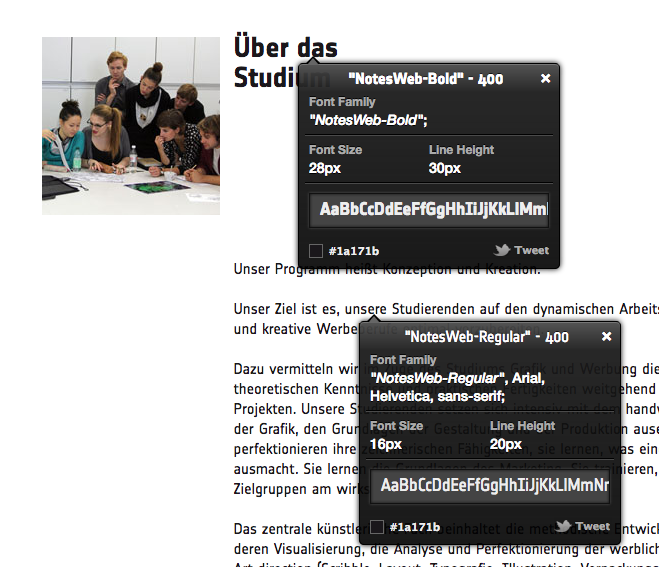
Welche Font ist auf dieser Homepage? (Klasse für Ideen)
Ich habe mir überlegt meinen Text bei meiner Bewerbung an deren Homepage anzulehnen. http://www.klassefuerideen.at/Studium.6.0.html
Dazu hätte ich aber 2 Fragen:
1. Um welche Schriftart handelt es sich hier bei Überschriften und Fließtext?
2. Empfindet ihr die Schrift als passend für die Bewerbungsmappe?
Ich bin mir nicht im klaren ob diese nicht vordergündig wegen der Lesbarkeit auf  Monitoren gewählt wurde. Persönlich spricht sie mich nicht so an, wirkt irgendwie kühl auf mich. Ich tue mir aber noch sehr schwer Schriften richtig zu beurteilen.
Selbst würde ich vermutlich die Open Sans Semibold oder Cambria wählen. Was haltet ihr davon?
"NotesWeb-Bold" und "NotesWeb-Regular".
Ich vermute eher weil Sie auch im Logo verwendet wird.
Gegen Deine Vorschläge spricht nichts, probiers doch mal aus ...
Ja genau es geht um den Einsatz in meiner Bewerbungsmappe also im Print.
Ich habe habe mich vorläufig mal für die cambria entschieden da sie mich mehr anspricht. Werde mal schauen wie sie sich im tatsächlichen Layout dann macht :)